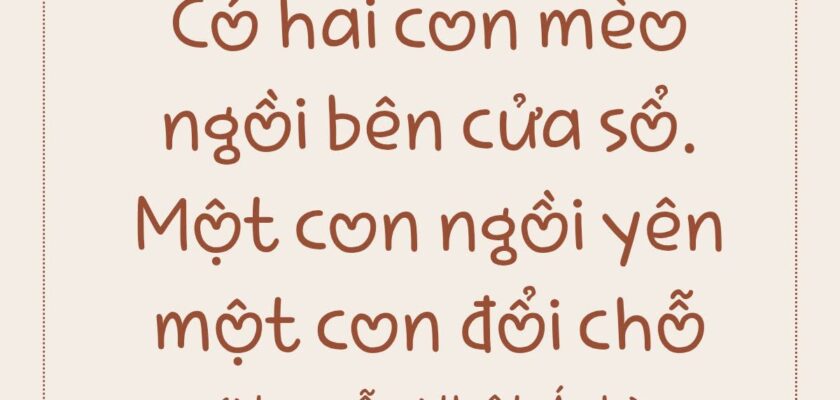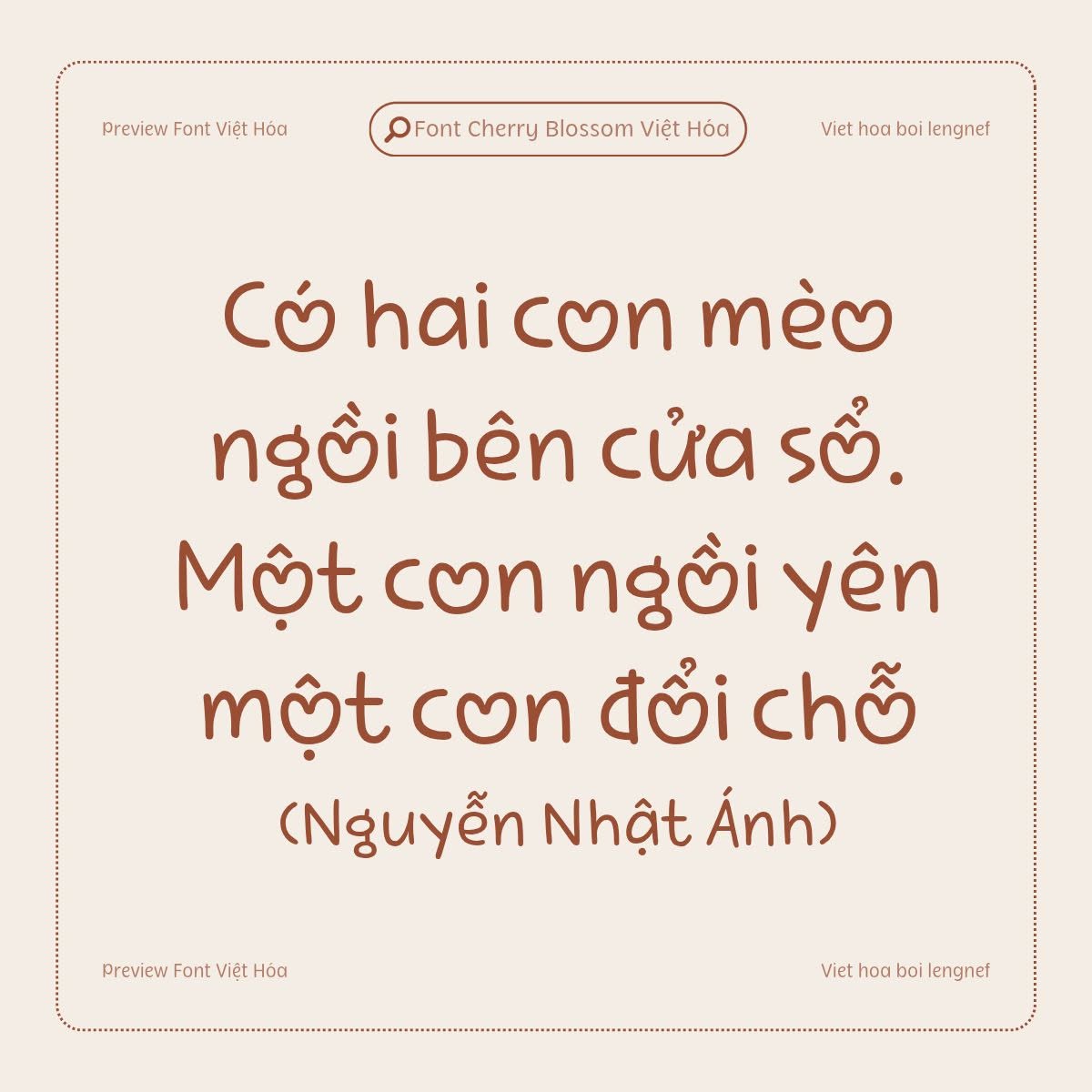
Việt hóa theo yêu cầu 20 || LF Cherry Blossom
Font LF Cherry Blossom Việt hóa
Cherry Blossom là kiểu phông chữ viết tay dễ thương, tất phù hợp với các dự án cute.